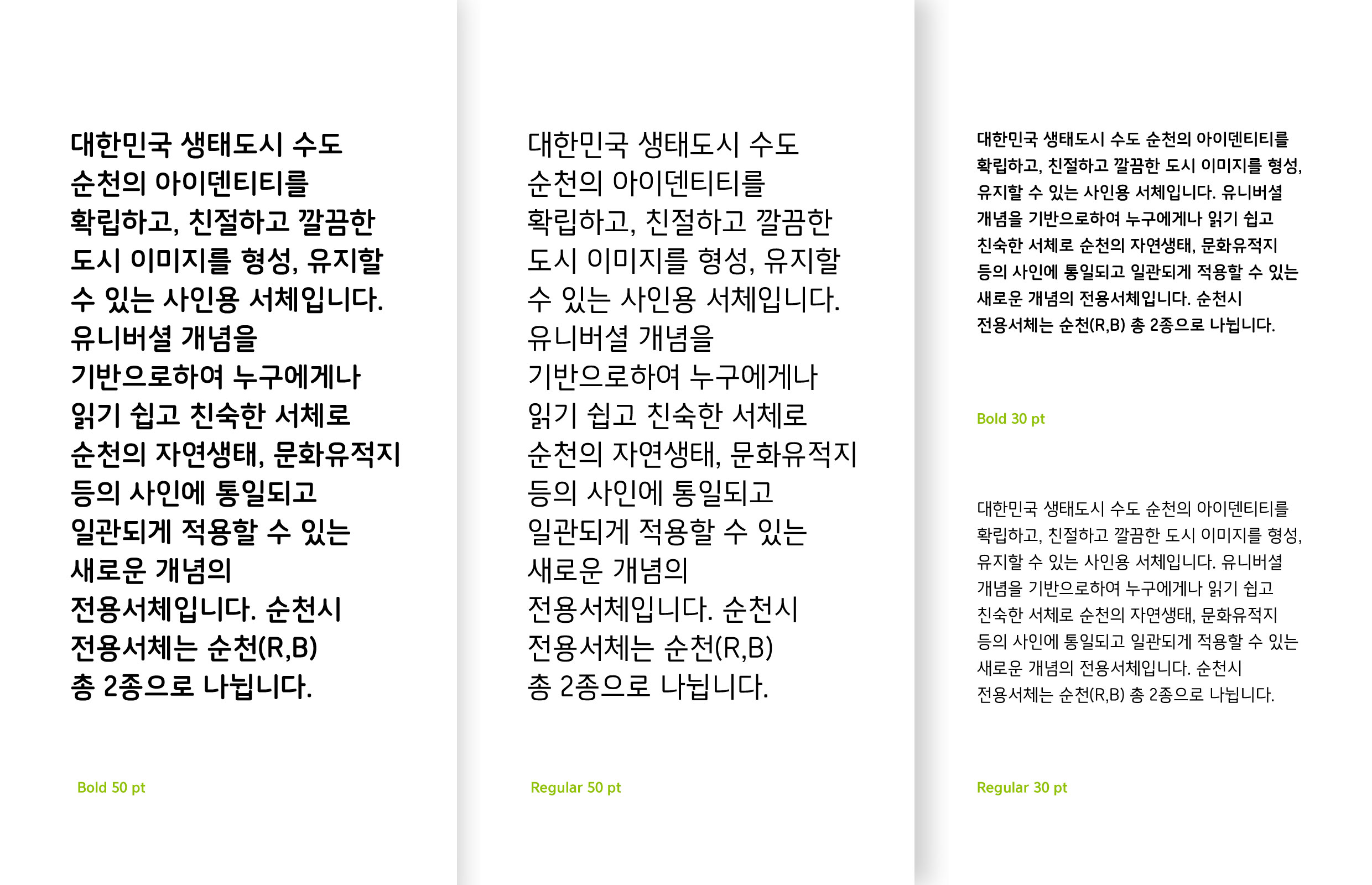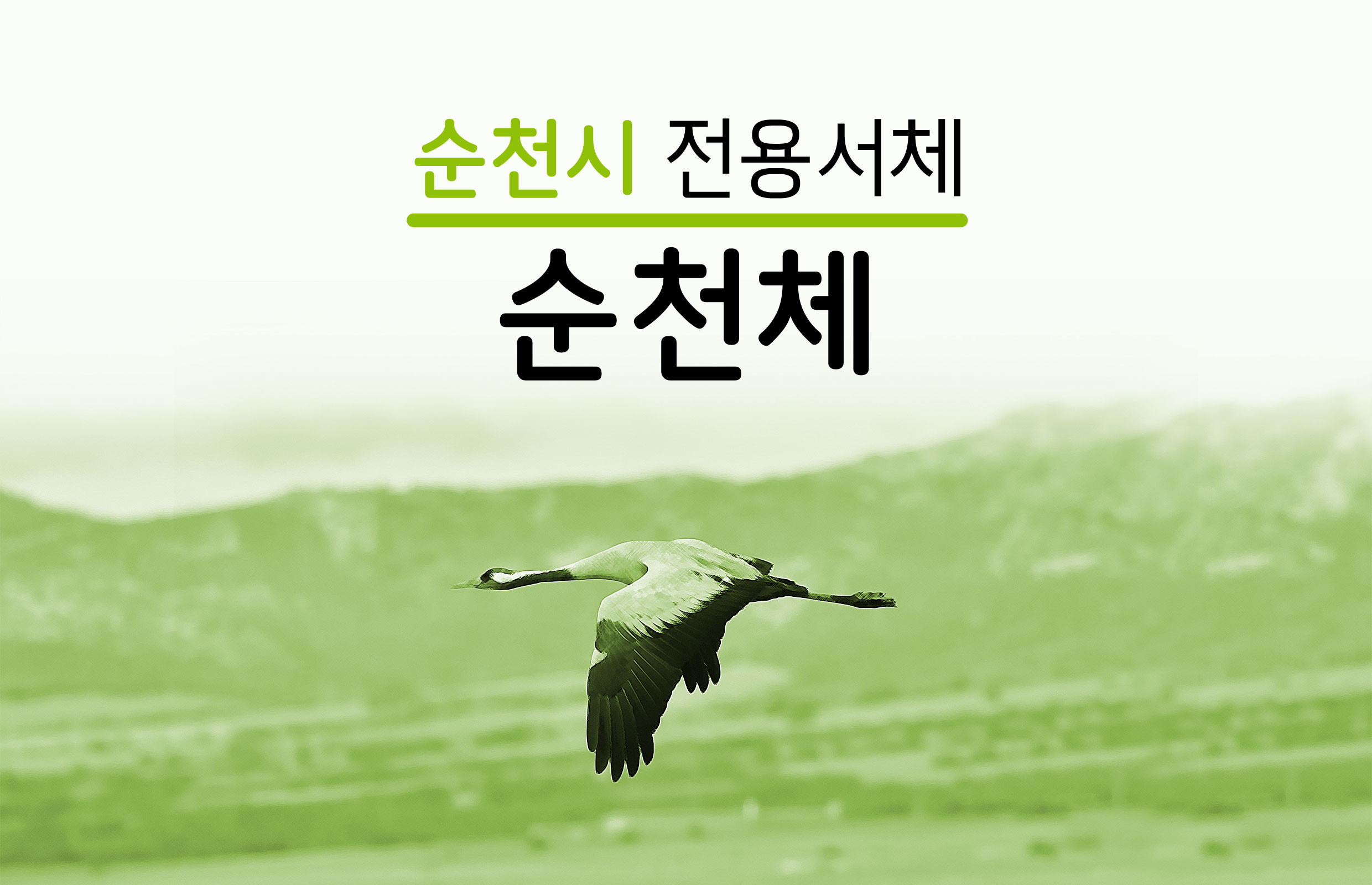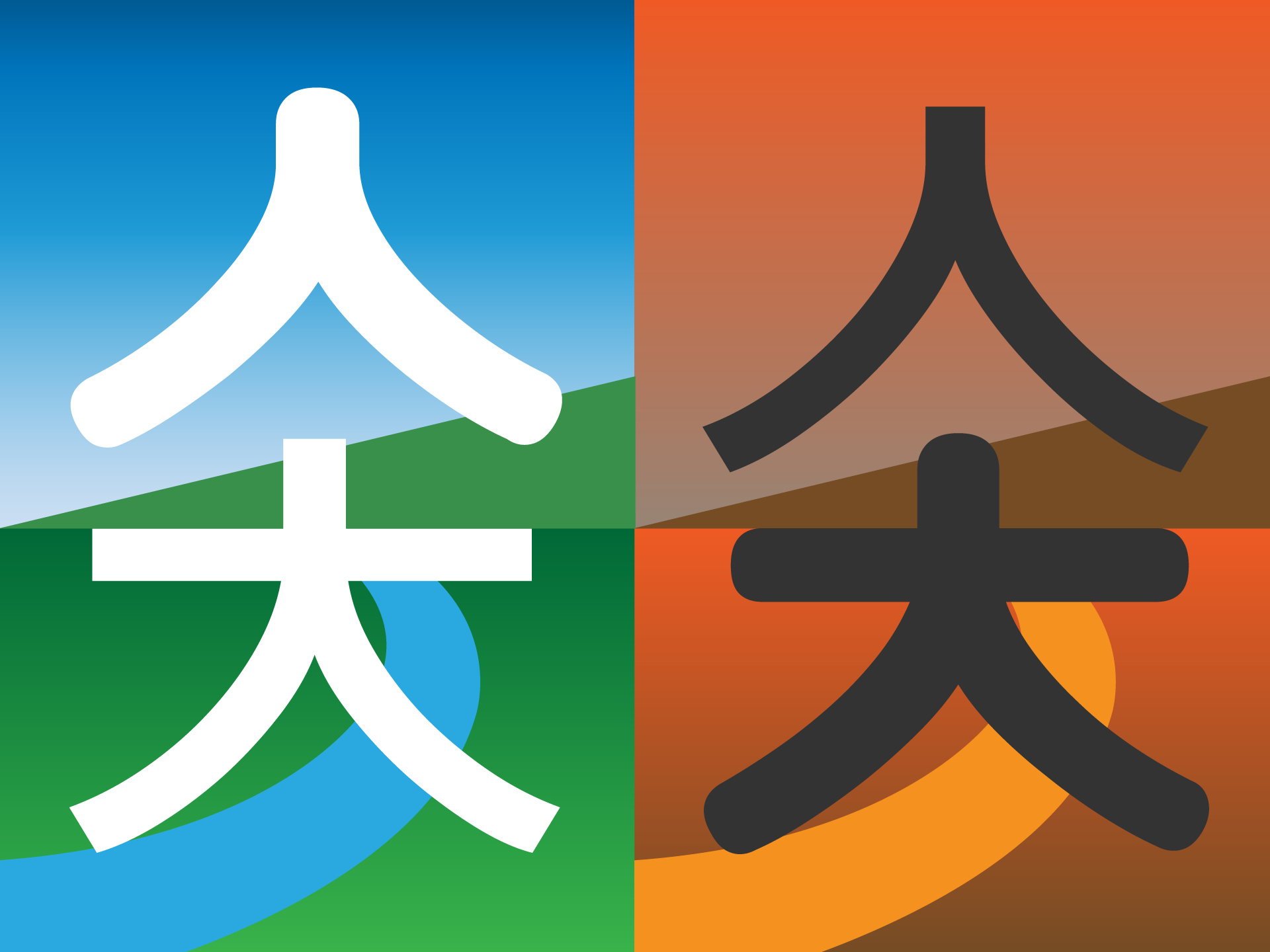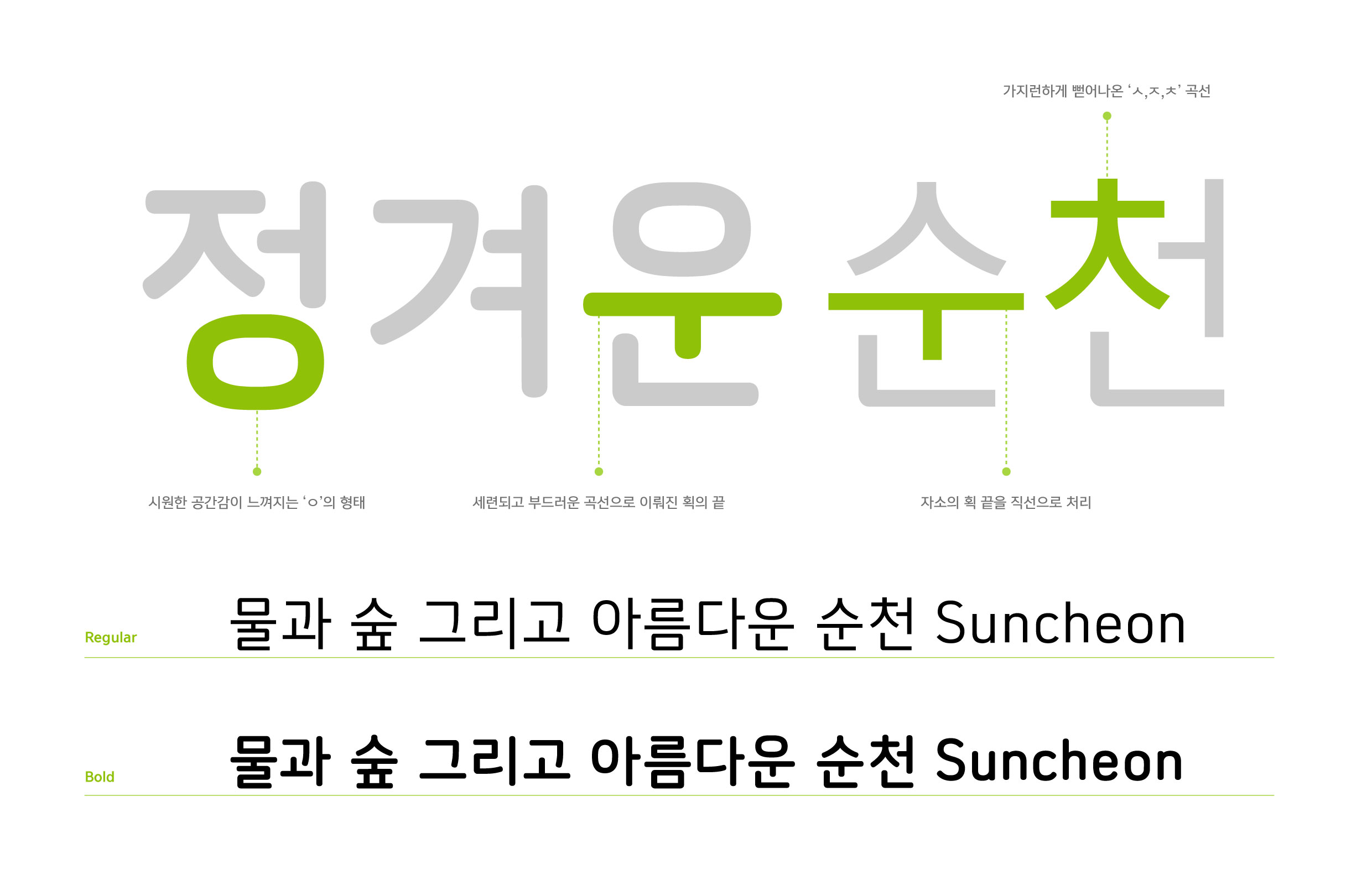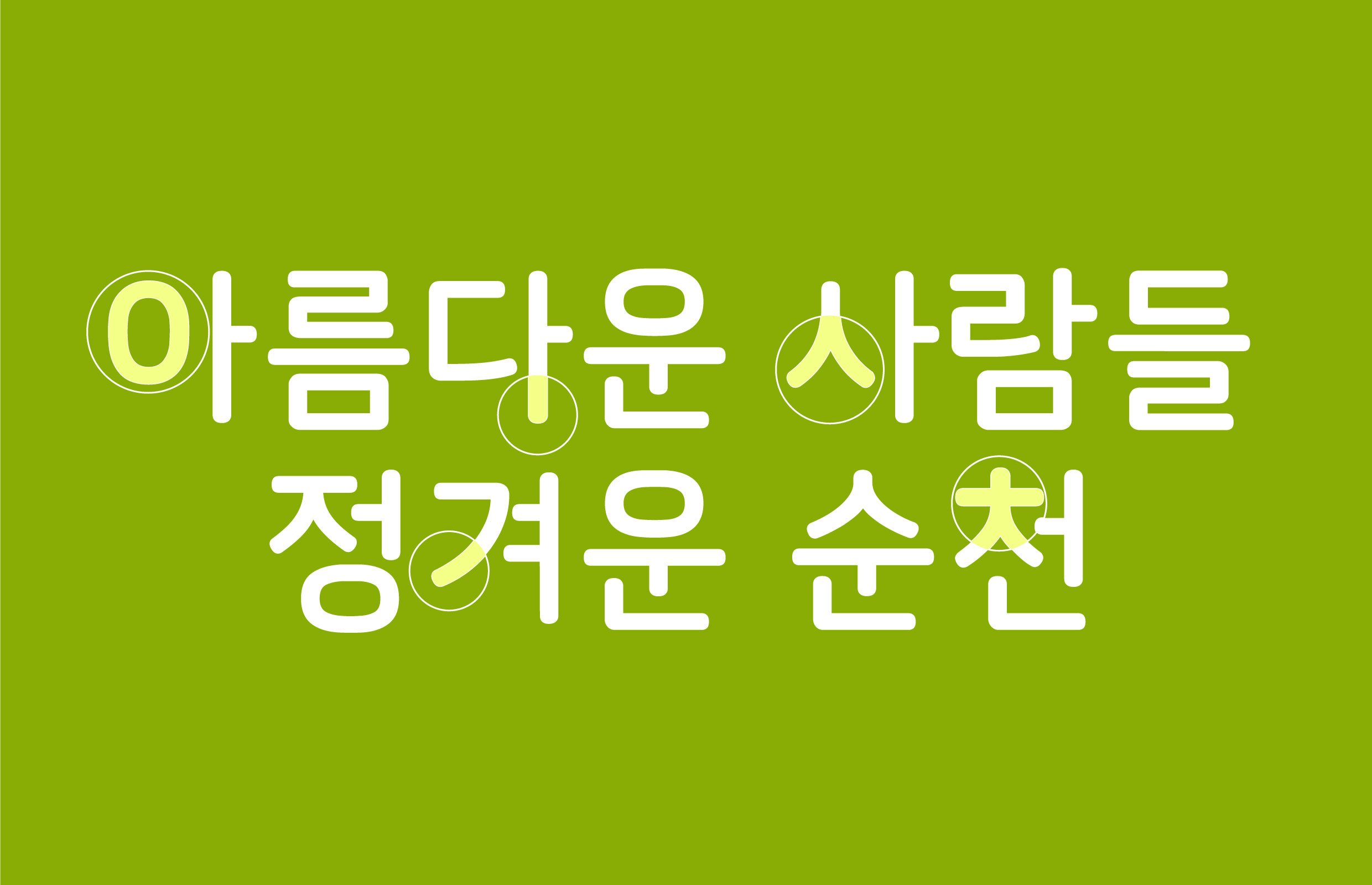
순천시
순천시 [순천체]
‘대한민국 생태도시’ 순천의 아이덴티티를 확립하고, 친절하고 깔끔한 도시 이미지를 형상화한 서체다. 순천만의 넉넉함과 원형 습지의 모습을 형상화한 ㅇ꼴의 형태와 ㅅ, ㅈ, ㅊ의 가지런하게 뻗어나가는 곡선은 하늘의 순리를 따르는 '순천'의 뜻을 담았다.